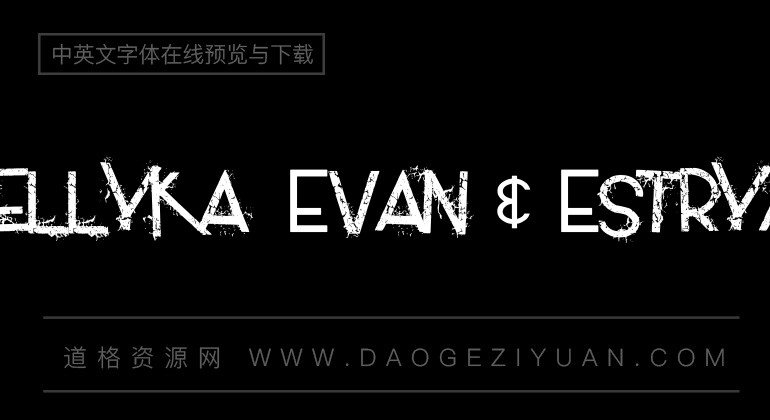
Jellyka Evan & Estrya 是一款英文字体,由著名的字体设计师Jellyka Nerevan设计。它是一款古典风格的字体,以其精致的细节,流线型的字形和温暖的色调而闻名。它具有大量的丰富多彩的符号,可以用于各种设计项目,如海报、书籍封面、信纸、网页设计等。它的设计灵感来自于古老的绘画,具有传统的艺术气息。内容介绍
Jellyka Evan & Estrya是一款非常不错的手写艺术字体,具有很好的视觉感,适合于文化类的宣传设计、商业类品牌的广告和产品包装设计以及个性化文字排版等较多场景。